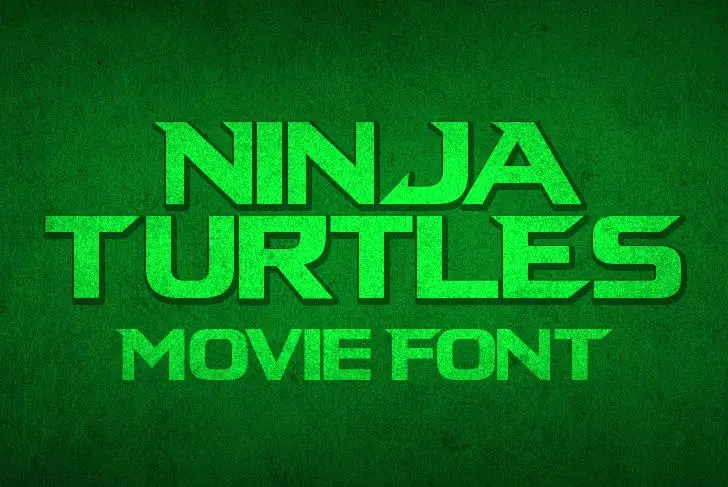
Ninja Turtles Font – Download Grátis
Aqui está uma versão de 2 parágrafos curtos para a descrição do download da font ‘Ninja Turtles Font’, mantendo o tom informativo e convidativo, sem inovações sobre características da font: Aproveite a atmosfera icônica dos Ninjas em sua próxima criação digital com Ninja Turtles Font. Desenvolvida por Fabi Mainier, esta elegante fonte do tipo Blackletter inspirada nos personagens lendários se encaixa perfeitamente para títulos de arte, rótulos de produto ou qualquer projeto que busque um estilo sóbrio e vibrante. Seu design robusto e atraente fazê-la uma opção versátil para aplicar em qualquer meio da sua escolha, como logotipos, bandas sonoras de jogos digitais ou até mesmo como um toque distintivo nos documentos impressos. Ninja Turtles Font é mais do que apenas uma fonte; ela é uma maneira de incorporar a energia e o encanto dos personagens em seu trabalho. Seja você designer gráfico, ilustrador ou criador digital, essa elegante escolha pode transformar sua marca ou produto de forma única e imponente, com um toque que não pode ser ignorado.
Designer: fabi.mainier